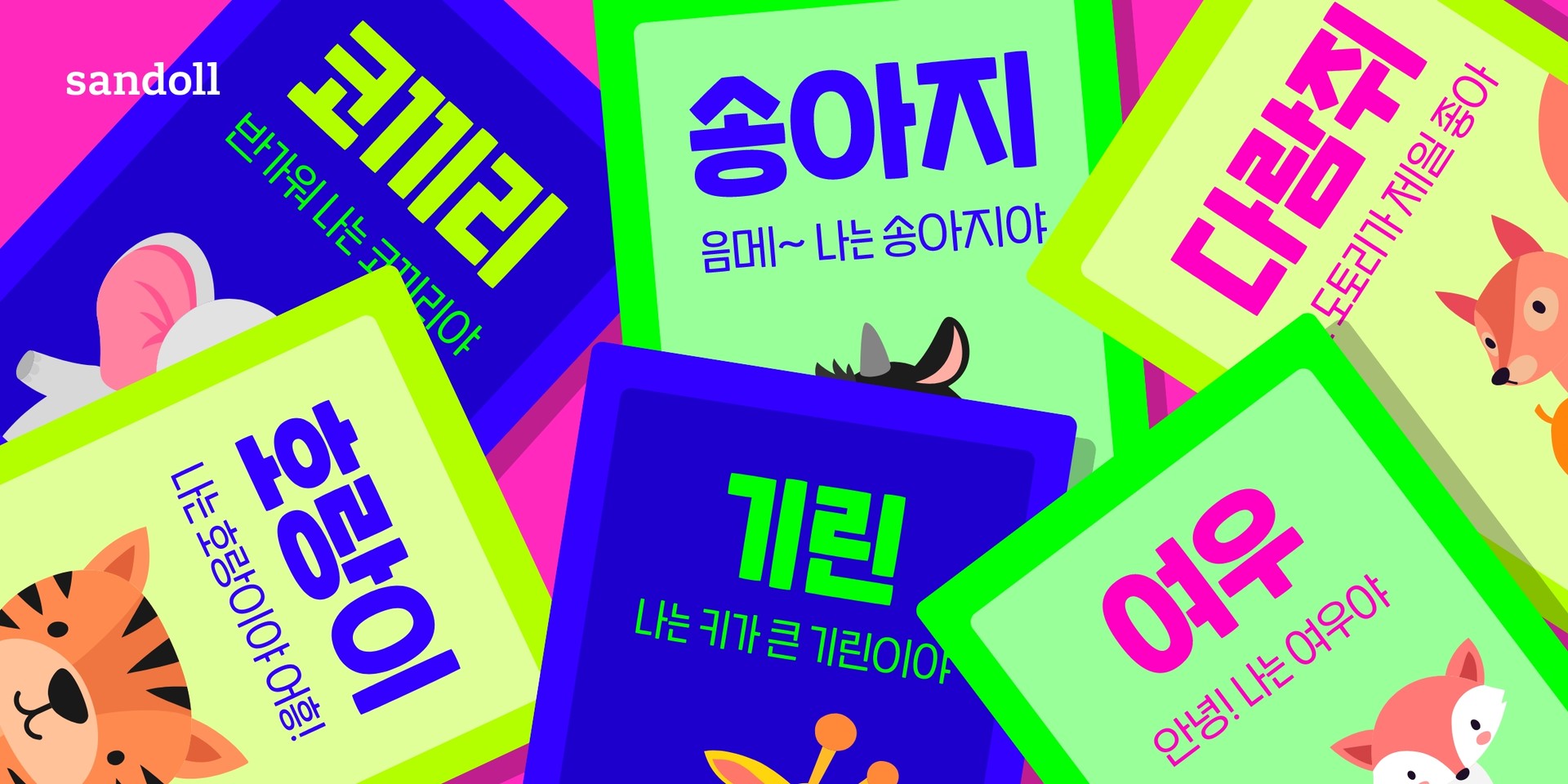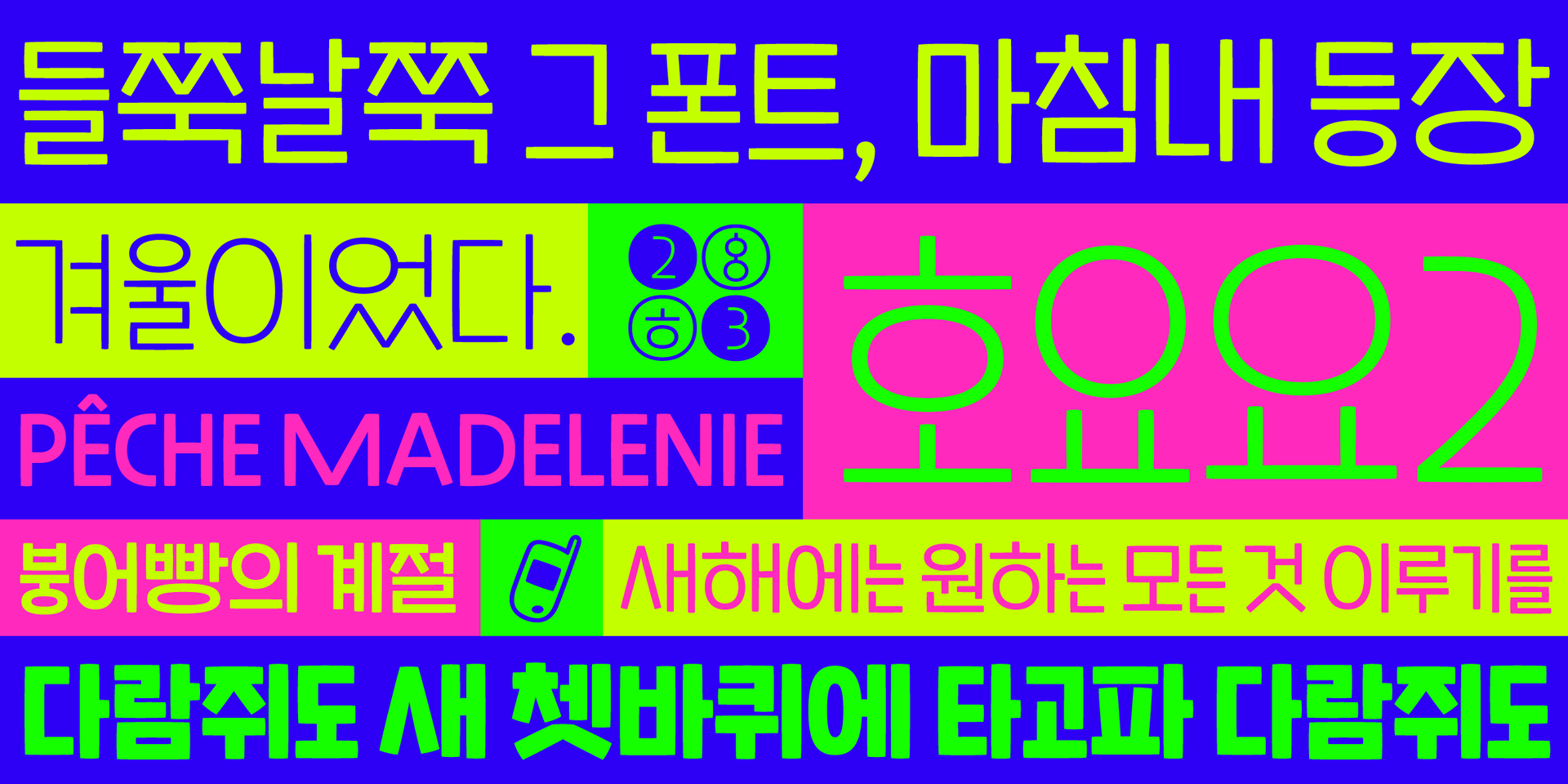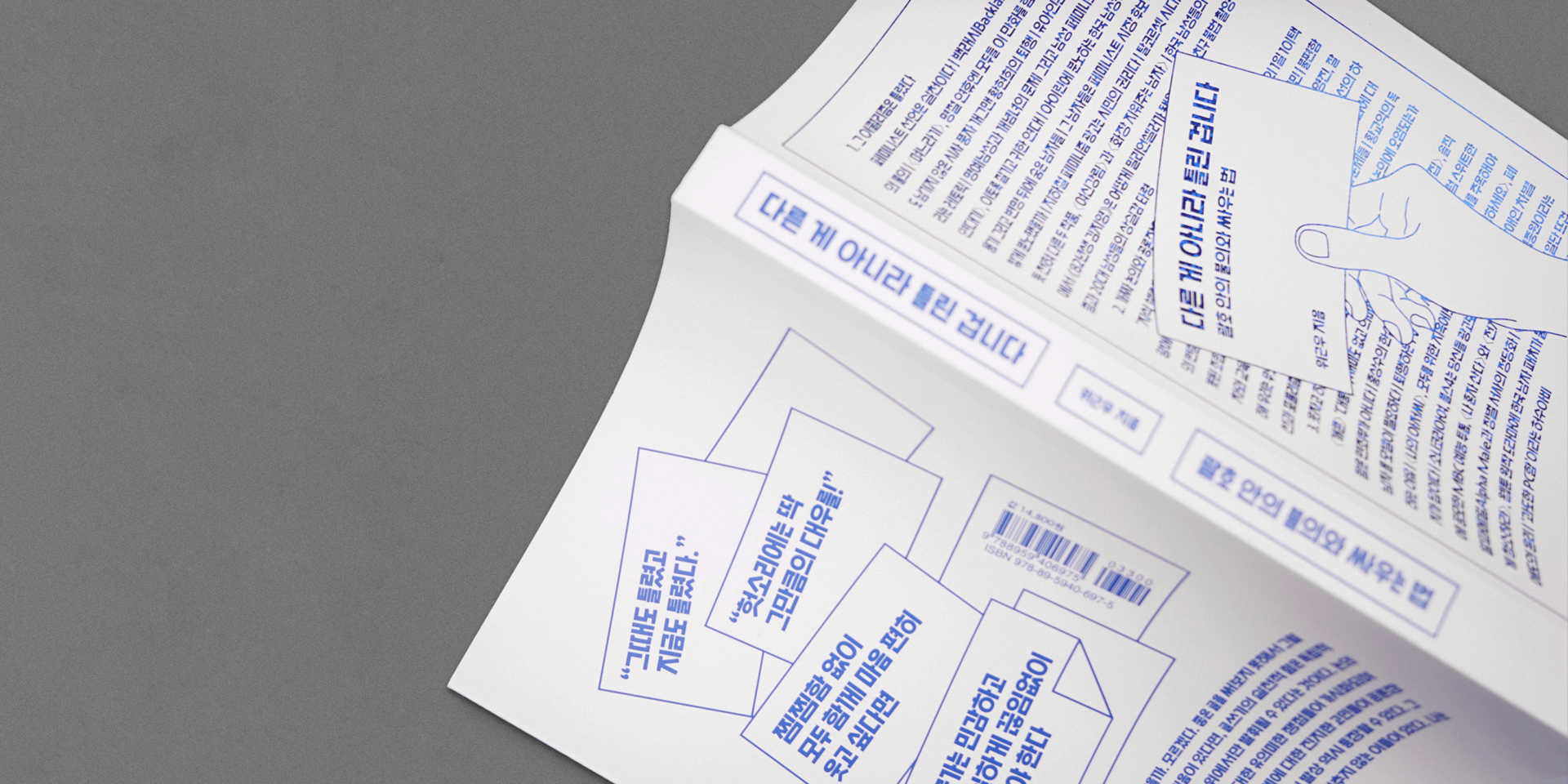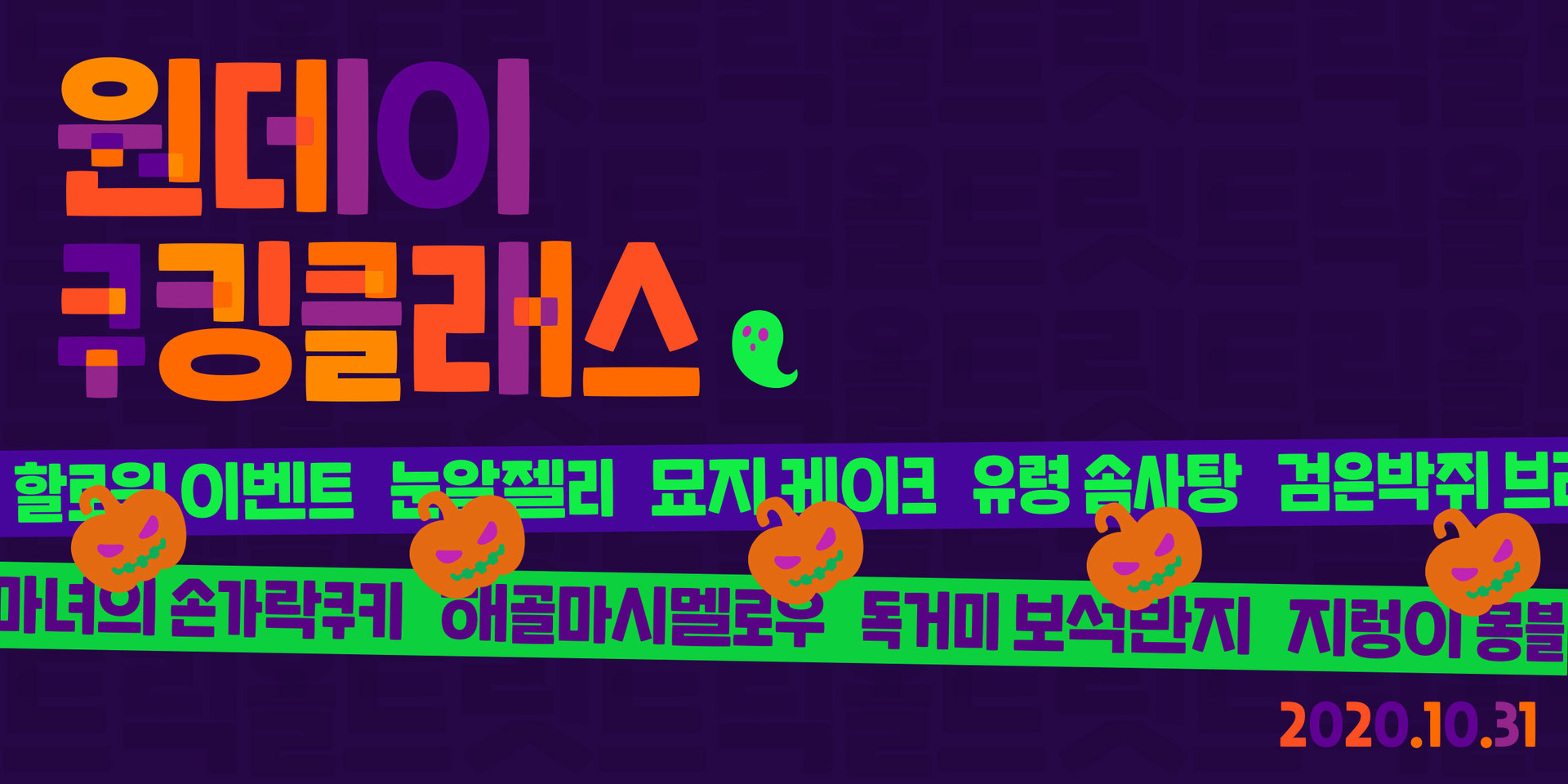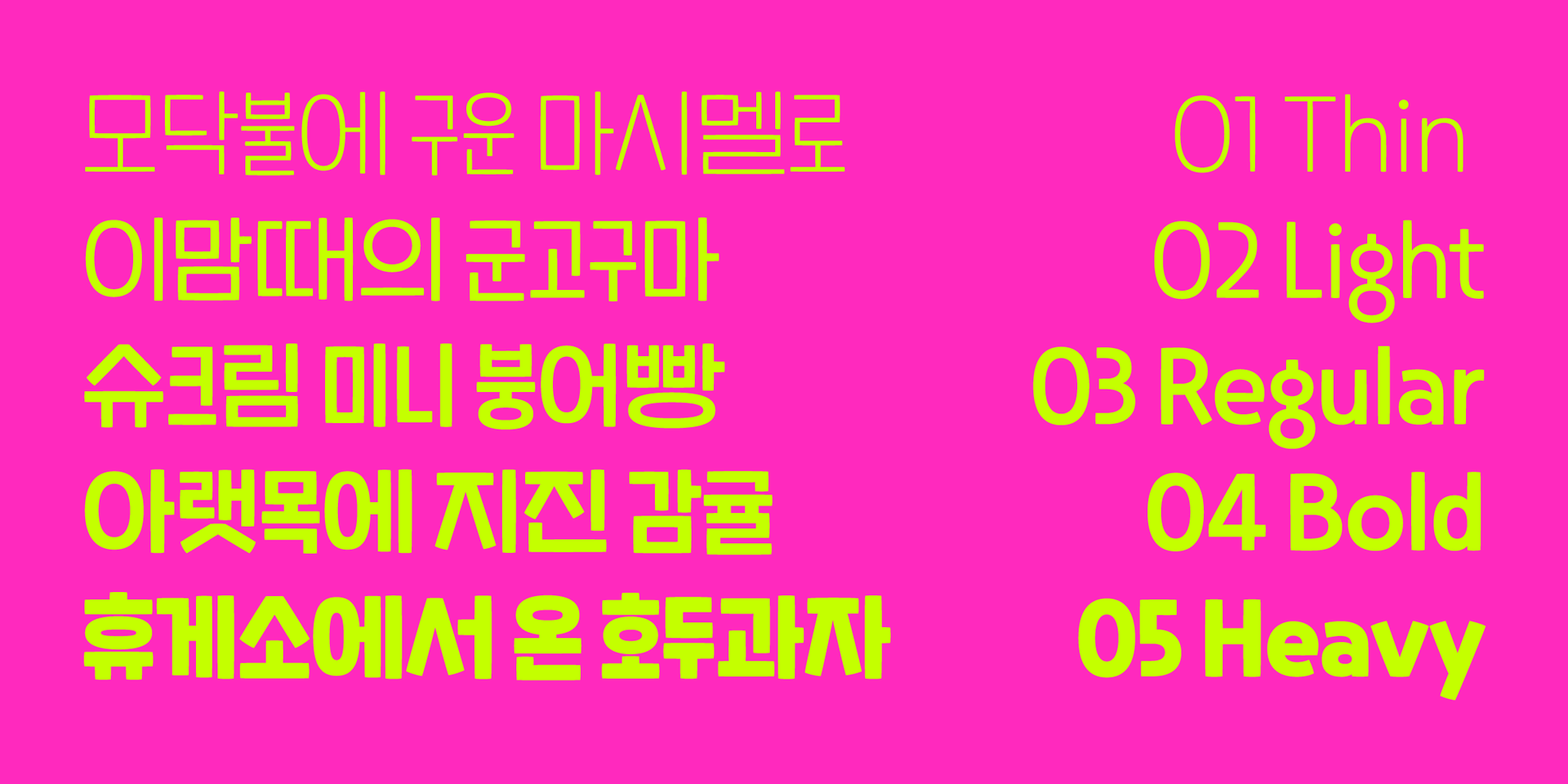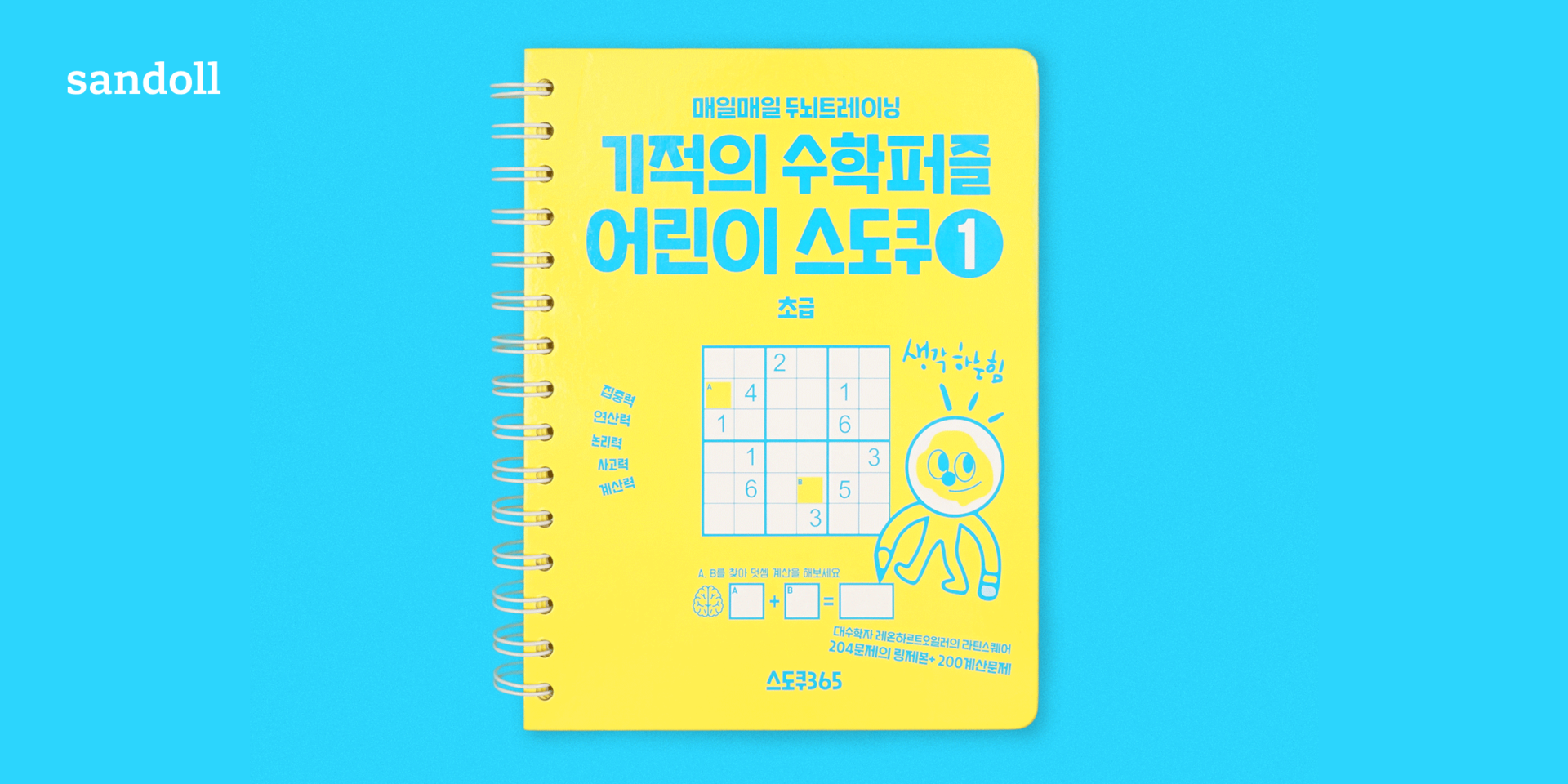
Sandoll 호요요
산돌 호요요는 산돌에서 최초로 시도하는 가변폭 폰트입니다.
기존에 선사하지 못했던 새로운 경험을 줄 수 있는 실험적이고 유쾌한 서체를 생각하며 제작했습니다. 틀과 형식을 깨는 파격적인 폰트인만큼 폰트의 이름 또한 특별한 의미를 담는 것이 아니라 같은 글자가 반복적으로 입력될 경우 가변폭이 적용되는 폰트의 특징에서 따왔습니다.
꽉 찬 네모꼴을 기본으로 하지만 타이핑 할 경우 예측할 수 없는 가변폭을 갖고 있으며 같은 글자를 반복 입력했을 때도 동일한 효과가 나타납니다.
Sandoll 호요요: 박부미, 김민정
Sandoll 호요요Color: 박부미
Sandoll 호요요2: 박부미, 성준석